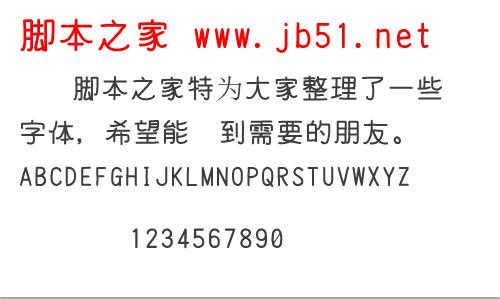
这款猫猫朋友体改二则是之前介绍的猫猫朋友体的修改版。这款字体把猫猫朋友体的爱心形状去掉了。虽然这是一款日本设计师制作的字体,但是所包含的中文字型还算比较多的。其中含JIS第1水准2965字,第2水准6355字+IMB扩张字体+日本教育汉字等,约6900个中文字。而且是可以免费商用无限制。
适合应用于艺术设计、平面宣传设计、网页设计,书法字帖等领域。